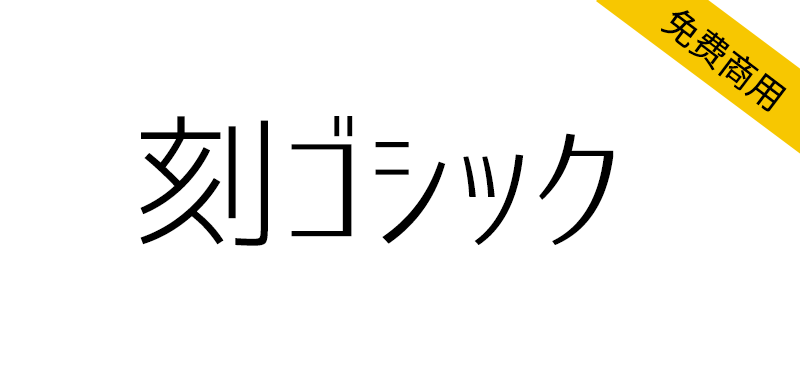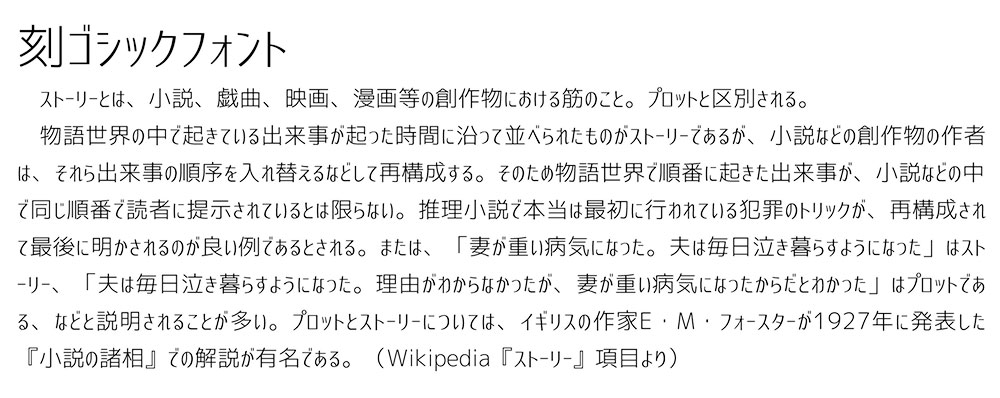
刻黑体(刻ゴシック)是一种结合了标准黑体字体与相矛盾的小平假名和片假名字符的字体。 与传统的平假名和片假名相比,线性形状是一个特征。 汉字的设计水平图像比垂直图像略薄。 这表达了一种轻盈而有节奏的氛围。
平假名和片假名保留其独特的形状,但不追求过于具体的设计,从而带来清新的效果。 合理平滑的曲线给人一种安全和稳定的感觉。 虽然假名与一般字体有很大不同,但它的设计目的是保留每个识别字符的特性,以免降低可读性。